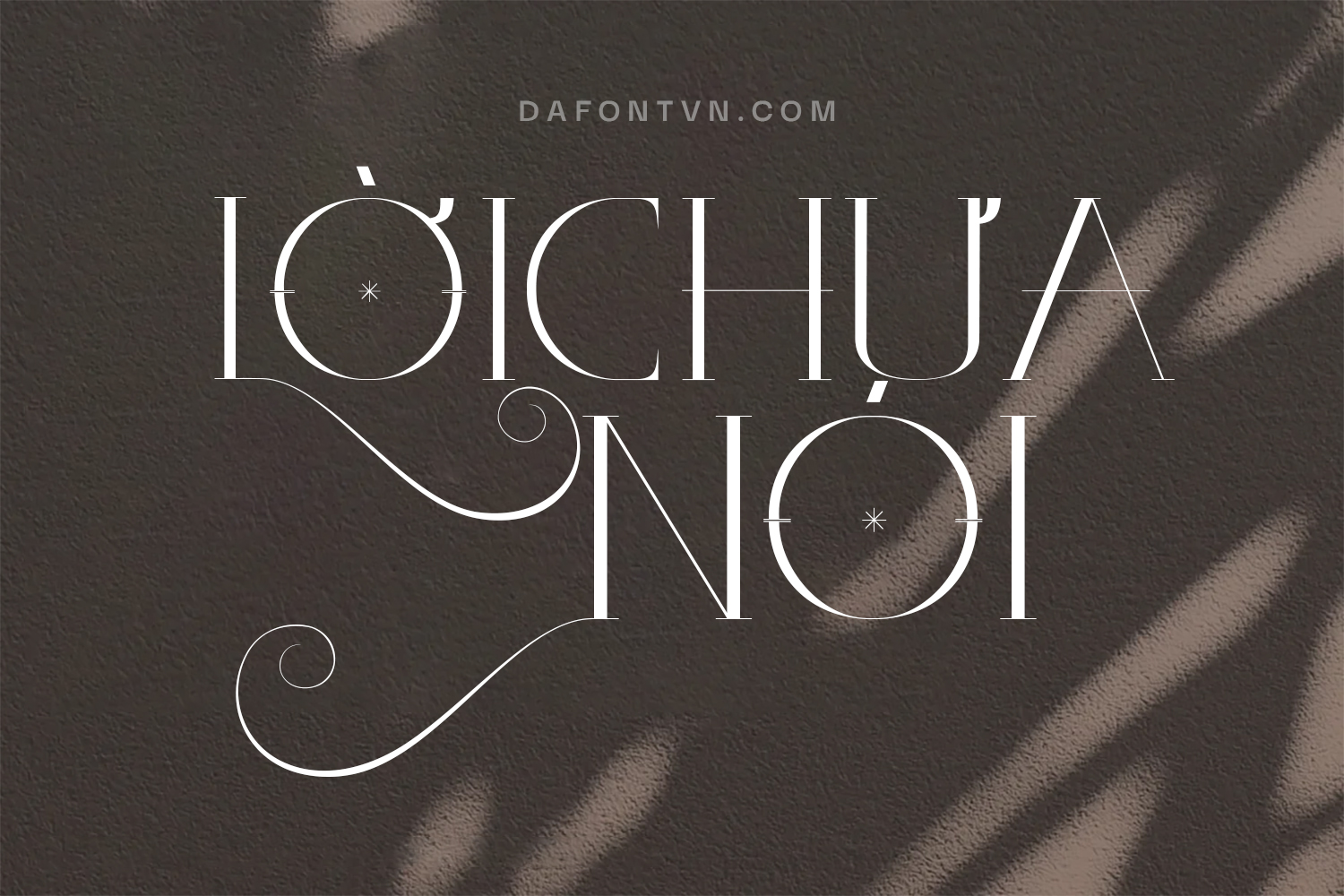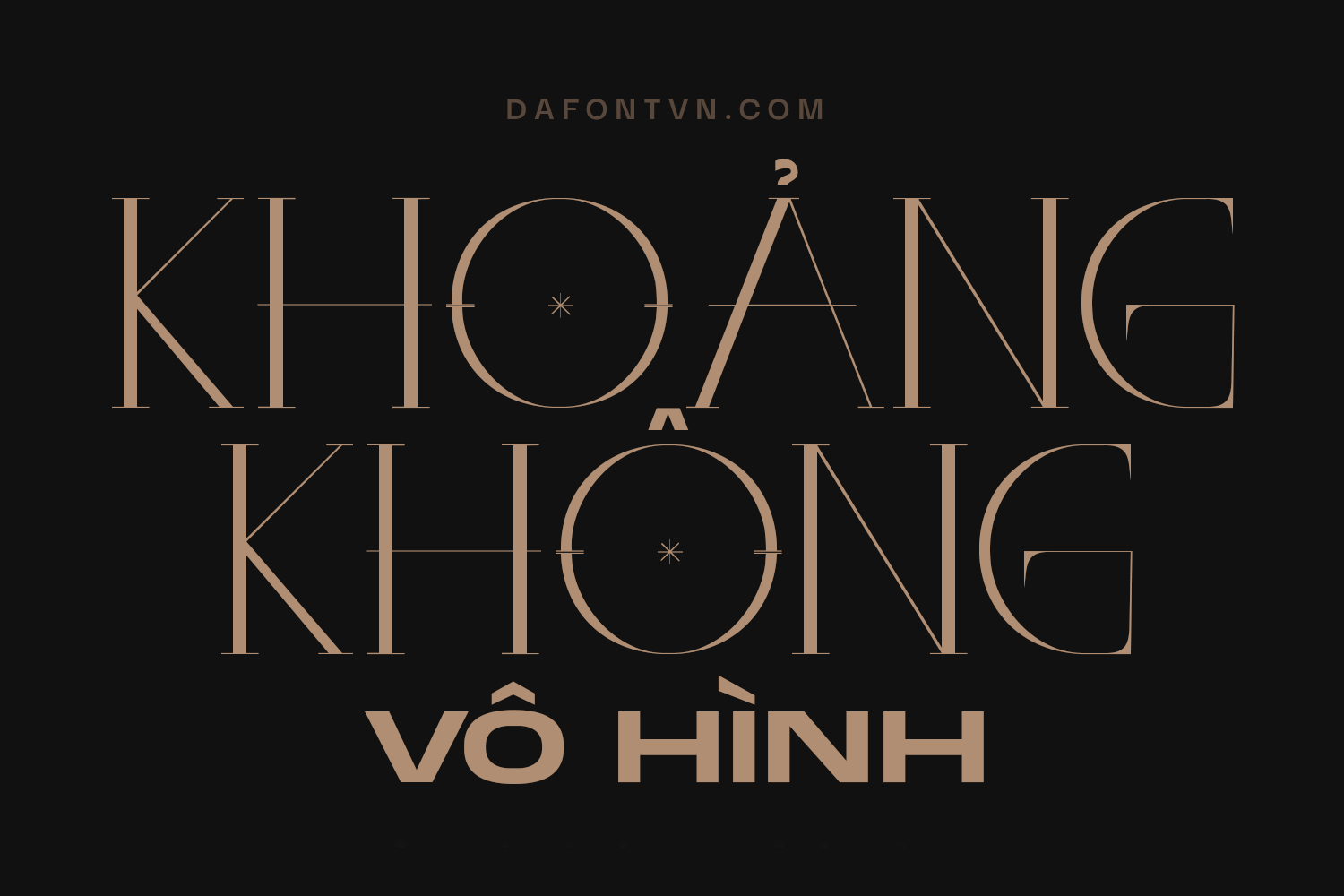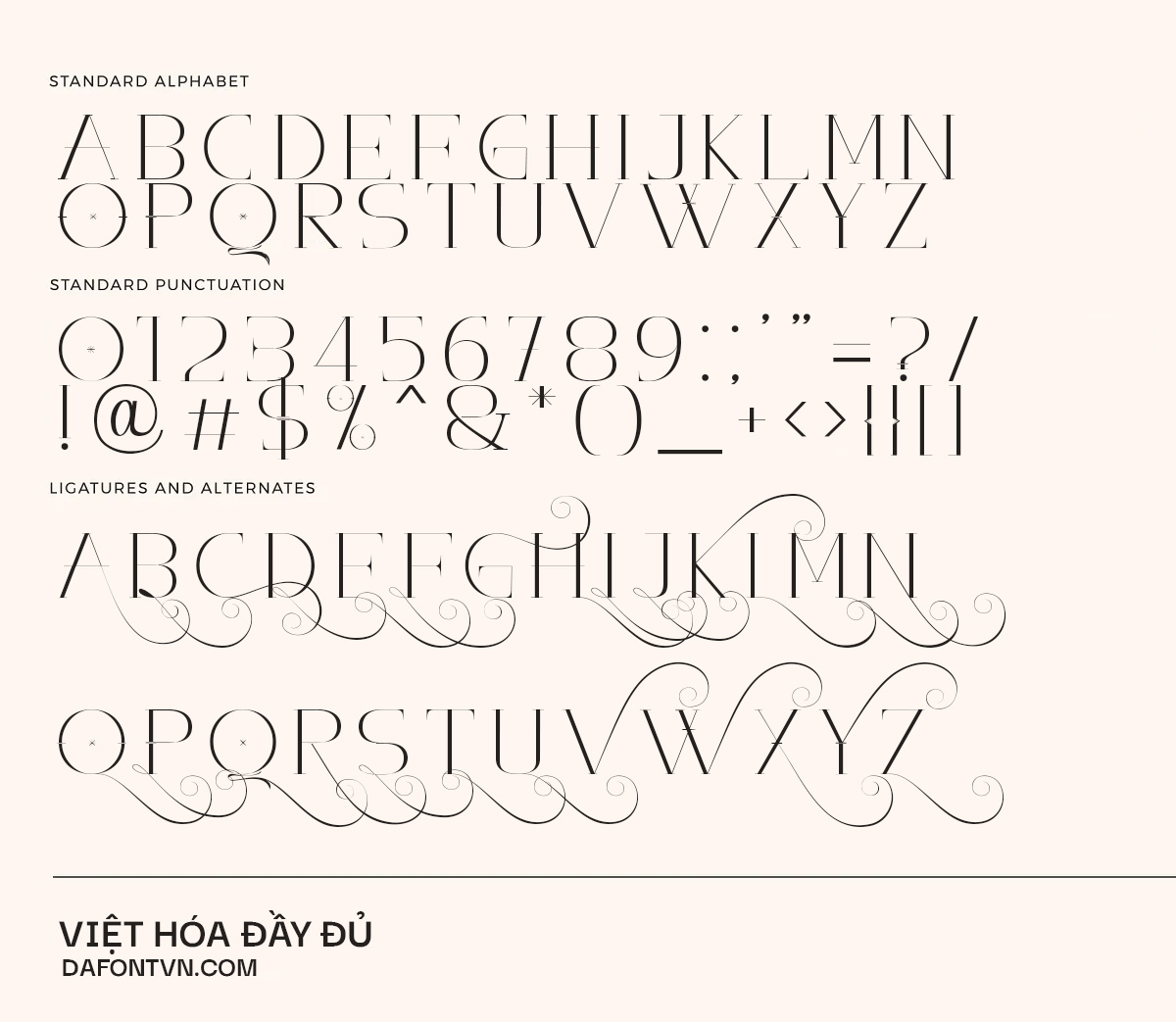
Font việt hóa Aloe Vera – Nhiều glyph đẹp
Aloe Vera Font là một kiểu chữ phong cách sang trọng và thanh lịch nó được thiết kế với các nét vẽ sang trọng mang đến những điểm nhấn ấn tượng cho bất kỳ dự án thiết kế nào của bạn. Với nhiều glyph đẹp bạn có thể lựa chọn để tạo ra những thiết kế độc đáo hơn.
Với các đường nét khá mỏng do đó phông chữ này phù hợp cho các thiết kế tiêu đề, typography, thiệp mời, bìa truyện, tạp chí…
Font Aloe Vera việt hóa đầy đủ, kerning và chỉnh sửa lại dấu cũng như tối ưu hóa và mã hóa PUA để sử dụng cho bất kỳ phần mềm nào.